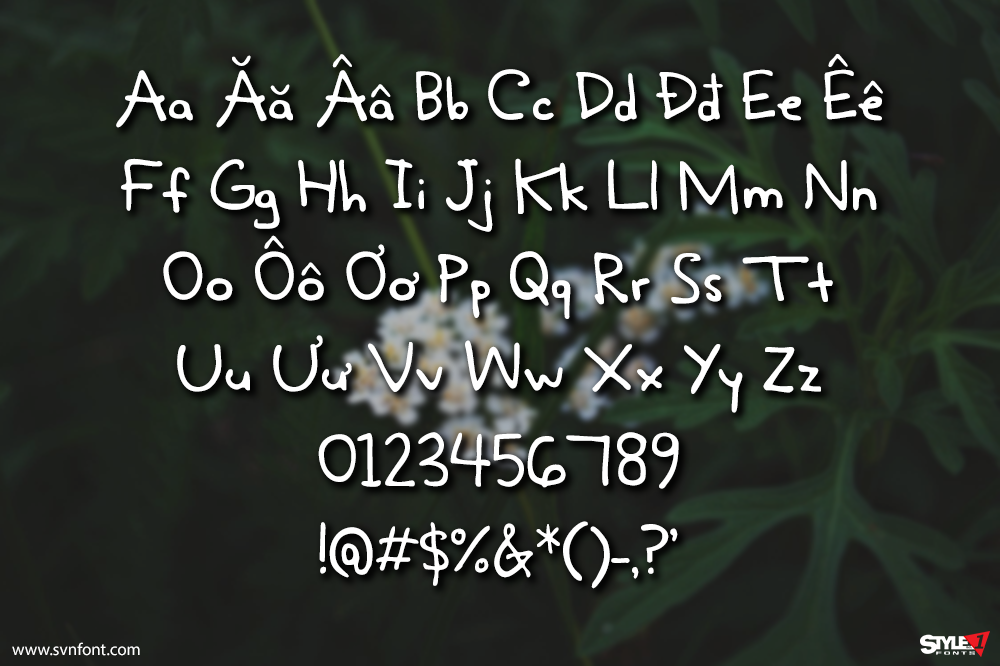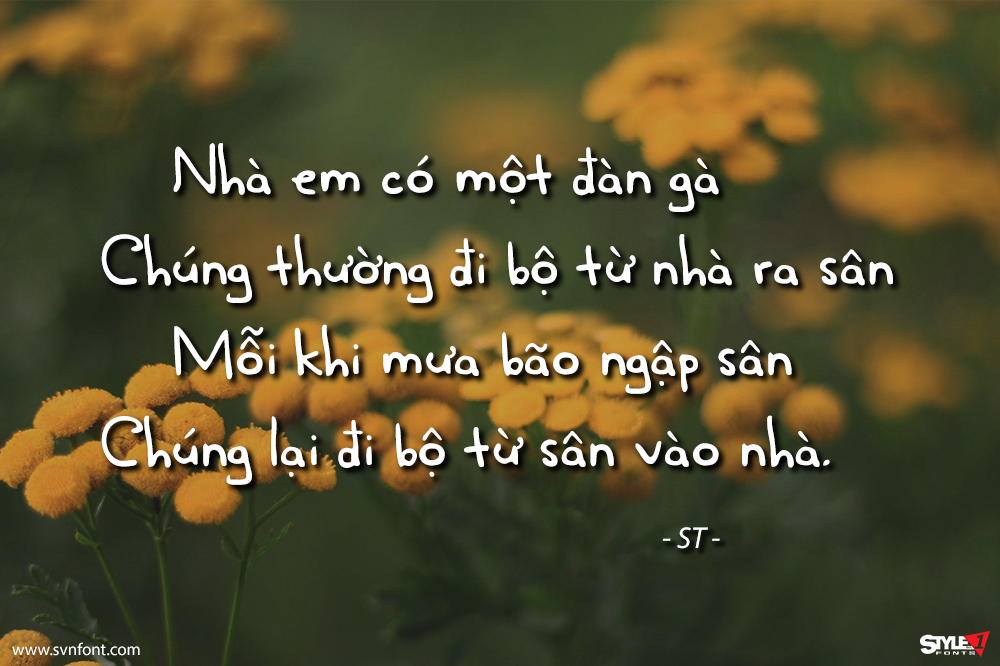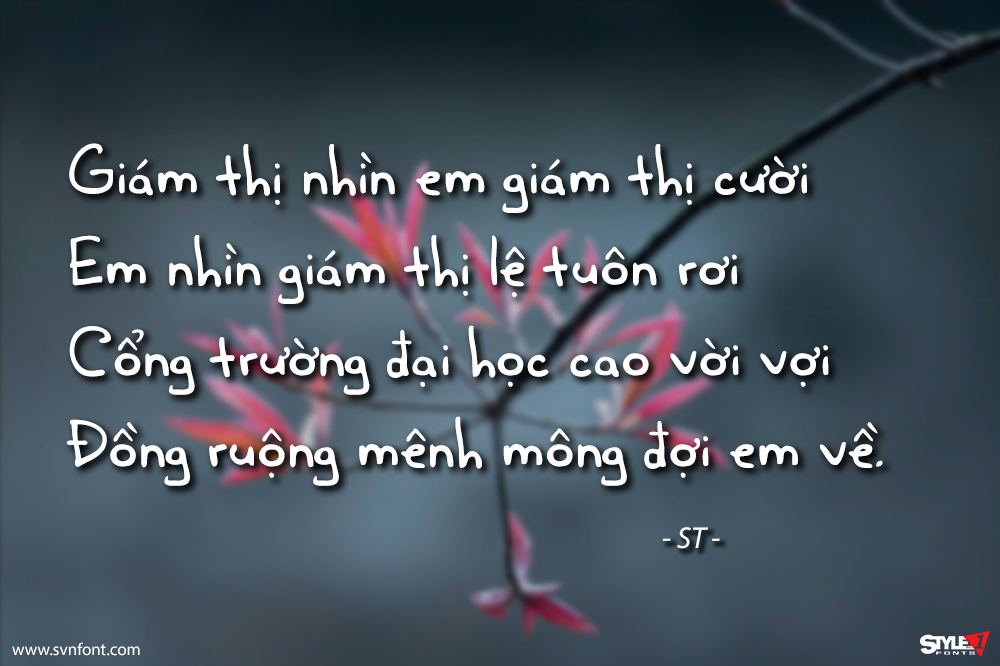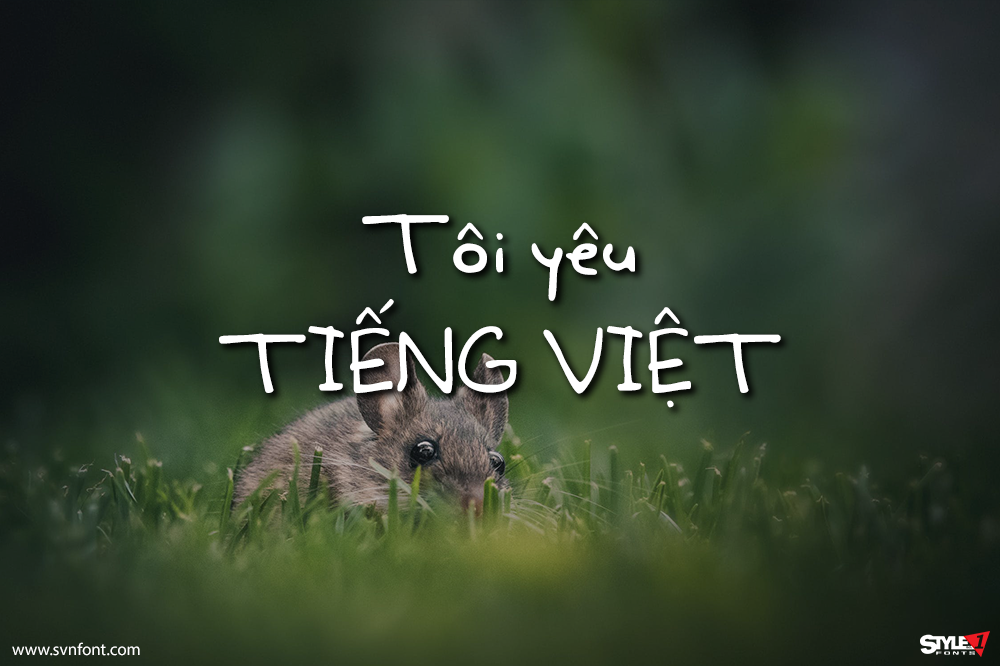
Pentastic là một font chữ in tay tự nhiên, được thiết kế để mô phỏng cảm giác viết bằng bút. Phong cách rõ ràng, dễ đọc nhưng vẫn dễ thương và vui nhộn. Pentastic sở hữu bộ ký tự mở rộng, bao gồm các dấu phụ Tây Âu và ligature, phù hợp cho môi trường và ấn phẩm mang tính quốc tế.
Nhà thiết kế: Natsuko Hayashida
Nhà phát hành: Okaycat